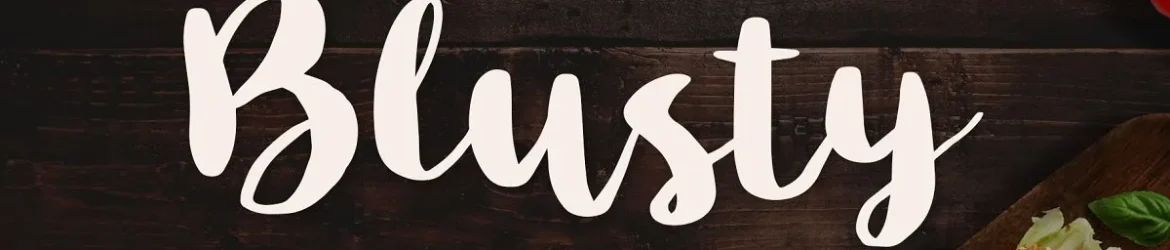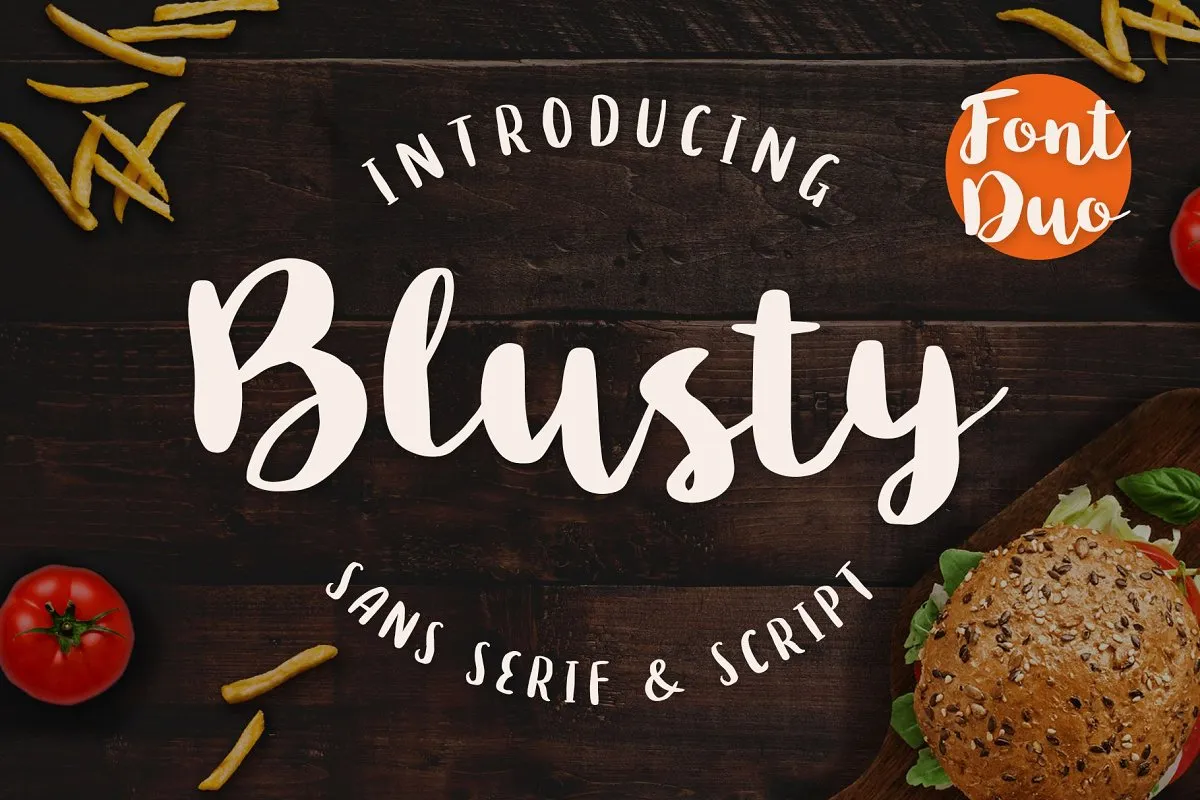
Blusty Font Duo
Introduzimos Blusty Brush Font Duo para você, criando uma experiência visual única e emocionante. Inspirado no estilo delicado dos traços manuscritos, esta fonte script é perfeita para dar um toque autêntico à sua arte digital. A Blusty Brush é uma criação de 24Design, que nos presenteia com esse trabalho cuidadosamente elaborado. Seja você um designer aficionado ou profissional, essa fonte oferece flexibilidade e criatividade para recriar qualquer design, transformando-o em algo inovador. A Blusty Brush adiciona um toque autêntico humano, proporcionando nuances sutis e detalhes meticulosamente construídos ao seu trabalho. Combina diferentes estilos da fonte de maneira personalizada, acrescenta ornamentos ou bandos para dar vida a qualquer frase, e até mesmo uma palavra simples ganha um brilho singular. Blusty Brush é sua oportunidade de explorar o poder criativo do design digital, com uma visão mais realista e convidativa. Não deixe que essa font se torne um objeto sem vida em seu próximo projeto; ela aguarda para ser transformada em algo extraordinário.